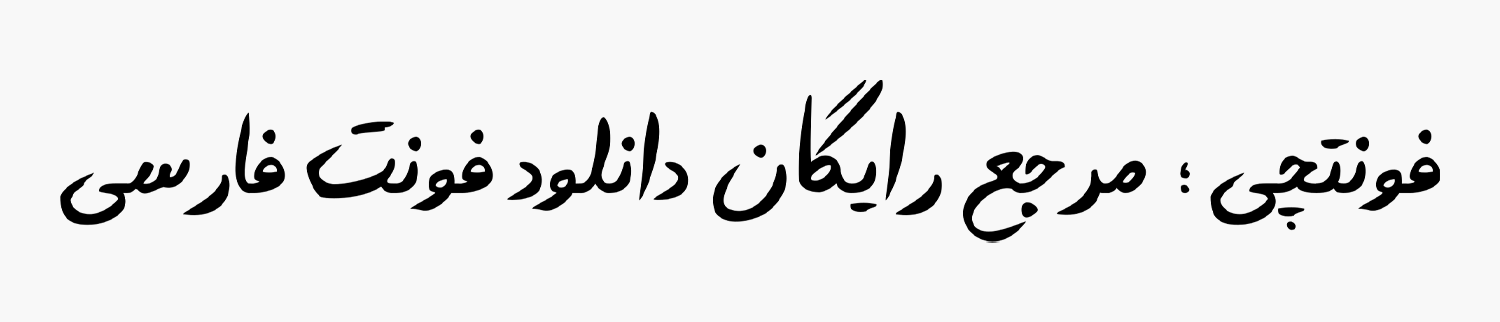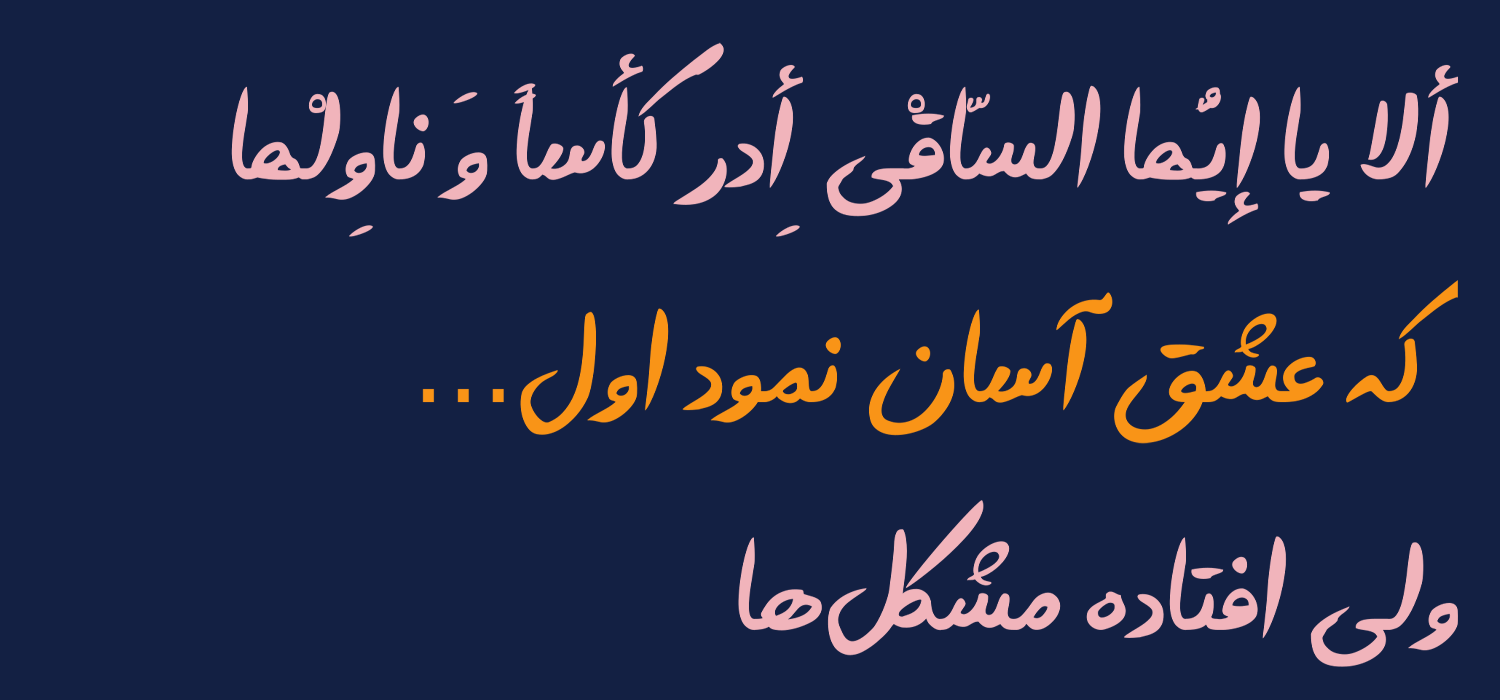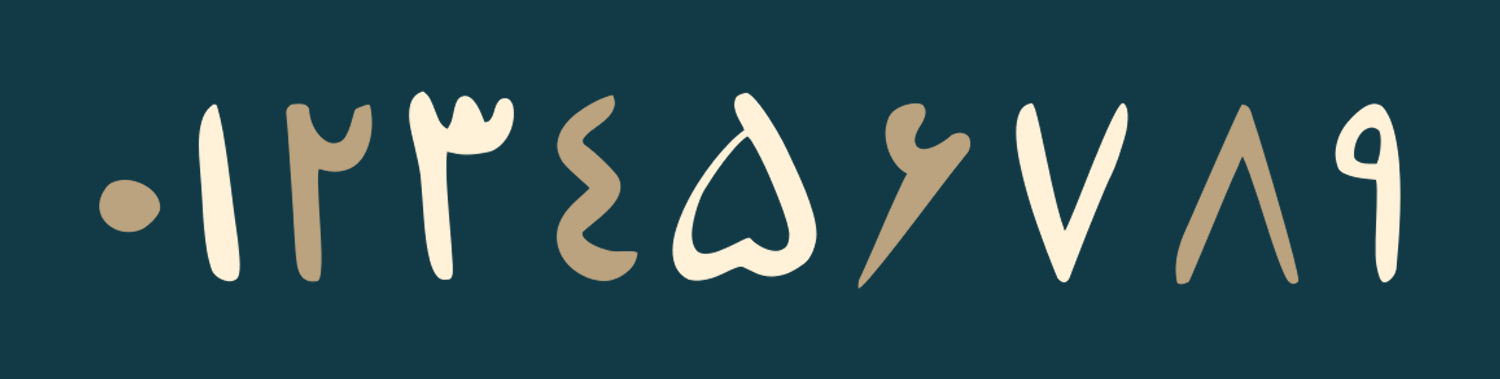
فونت فرامرزیان (Faramrzian)
فونت فرامرزیان (به انگلیسی: Faramrzian) قلمی در گروه فونتهای دست نویس با سبک آزاد است که با توجه به راجتی و ساختار گرافیکی که دارد میتوان از آن برای طراحی کارهای تبلیغاتی استفاده کرد که اصولا شامل تابلوهای فروشگاه، بنر شبکههای اجتماعی و این قبیل موارد میشود.
فاطمه فرامرزیان این قلم را در قالب یک پروژه دانشجویی در کارگاه طراحی قلم مسلم ابراهیمی، زیر نظر وی طراحی کرده است. این قلم بر خلاف سایر فونتهای دستنویس با الهام گرفتن از قلممو و جوهر ساخته شده است که همین ویژگی باعث شده در این گروه قلمها منحصر بهفرد باشد.
در ادامه این نوشته از سایت فونتچی قصد داریم به نقد و بررسی فونت فرامرزیان بپردازیم؛ قلمی که علاوه بر کارهای تبلیغاتی گرافیکی میتواند برای صنعت چاپ و مطبوعات، بهویژه طراحی جلد کتاب یا طراحی کتابهای مصور کودک و نوجوان مناسب باشد.
اگر قرار باشد قلمی نزدیک به آن را معرفی کنیم، شاید فونت آتابای با توجه به ساختار آزادی که دارد نزدیکترین فونت فارسی به این قلم باشد که پیش از این در سایت فونتچی آن را معرفی کردهایم.
سبک طراحی و وزن فونت فرامرزیان
این قلم کاملا منطبق با حرکات قلممو با استفاده از جوهر طراحی شده است؛ به شکلی که در تمامی حروف شاهد وزن یکسان نیستیم و همانطور که انتظار میرود در کشیدگیها، خطوط قائم و مورب شاهد کاهش ضخامت در بخش انتهایی هستیم.
نقاط در این قلم به همان سبک دستنویس که بسیاری از ما داریم ایجاد شده است که برای نقاط دوتایی بهصورت خطی و برای نقاط سهتایی برخی حروف مثل «ش، پ» به صورت گرد به هم پیوسته است. این قلم برای تایپ کاملا حس تایپ با استفاده از قلممو و جوهر را با توجه به پخش شدن جوهر بر روی کاغذ القا میکند.
پشتیبانی کامل از رسم خط فارسی
فونت فرامرزیان اصولا فونتی فارسی است که از این رسم خط پشتیبانی میکند و استانداردترین حالت استفاده از این قلم نیز برای زبان فارسی است. اما از آنجا که رسم خط زبانهای دیگری مثل عربی، کردی و اردو نیز همین است، میتوانید برای آن زبانها هم از این قلم استفاده کنید.
ولی مسئلهای که وجود دارد این است که برای آن زبانها، پشتیبانی از برخی حروف نظیر «ك، ي، ة، ؤ، ئ» به طور کامل وجود ندارد یا مثلا همانطور که در تصویر زیر میبینید اعراب برای زبان عربی دارای اشکالاتی جزئی هستند که روی حرف قرار میگیرند.
در حالی که پشتیبانی این قلم از زبان فارسی کامل بوده و تمامی فواصل و کرسیها برای حروف در حالت استانداردی قرار گرفتهاند.
این قلم از زبانهای لاتین مثل انگلیسی پشتیبانی نمیکند و زمانی که با این قلم تایپ انگلیسی انجام دهید، از قلم پیشفرض سیستم عامل برای تایپ حروف انگلیسی استفاده خواهد شد.
اعداد فارسی نیز در این قلم به همان شیوه قلممو و مرکب تایپ شدهاند که مشابه تصویر بالا امکان تایپ آنها را دارید. اما همانطور که گفته شد در صورت استفاده از زبان عربی، اعداد «٤٥٦» همچنان تایپ فارسی را خواهند داشت.
مناسب برای تبلیغات و مطبوعات
بهترین کاربردی که قلم فرامرزیان دارد، برای استفاده تبلیغاتی و کارهای گرافیکی در صنایع مختلفی مثل چاپ و کتاب است. از این قلم میتواند بر روی تابلو سردر فروشگاهها استفاده کرد که نمونهای از آن را در تصویر زیر میبینید.
با توجه به طراحی فانتزی این فونت میتواند در حوزه کودک و نوجوان نیز مورد استفاده قرار گیرد؛ که برای جلد روی کتاب، کتابهای مصور، کاتالوگ محصولات و دیگر موارد مناسب است. این قلم دست نویس ساختاری نرم و دوستانه دارد که در این حوزه اهمیت زیادی دارد.